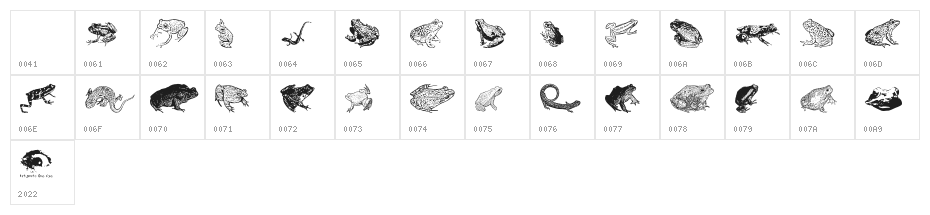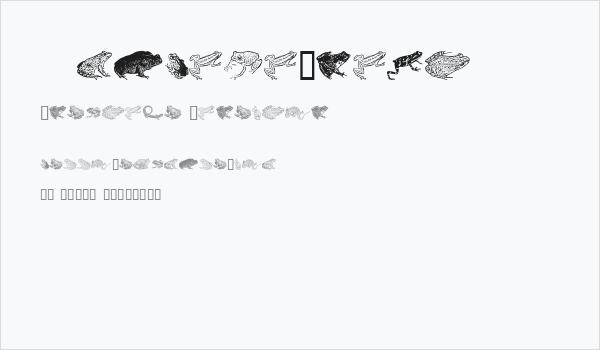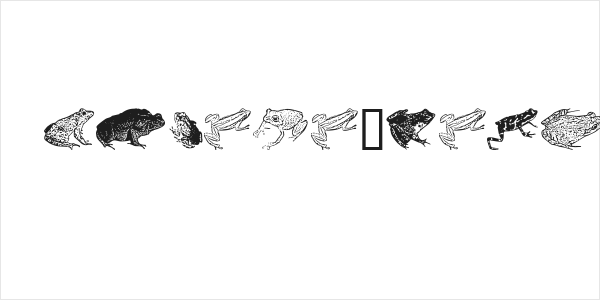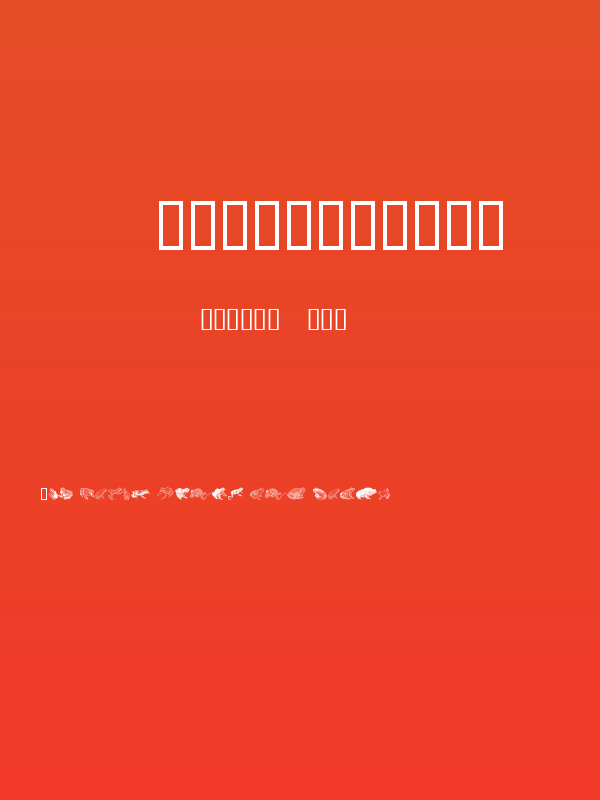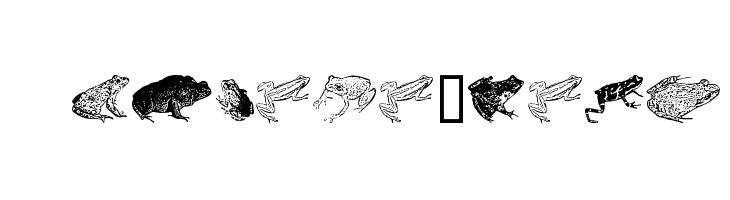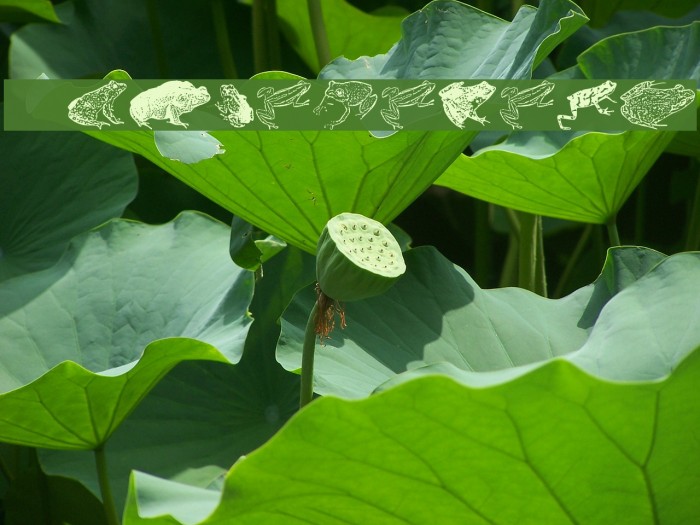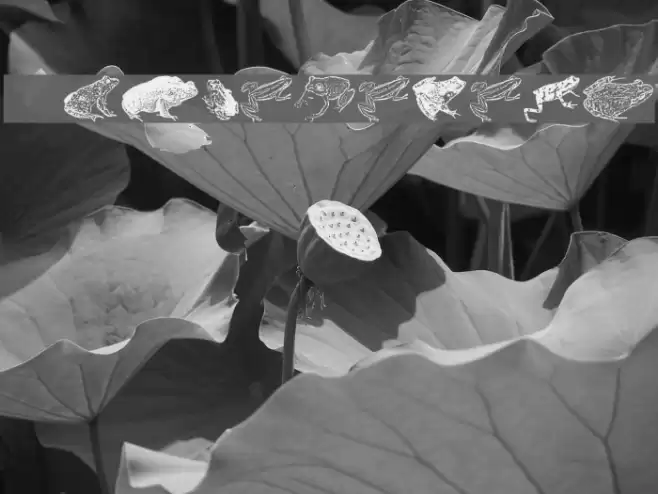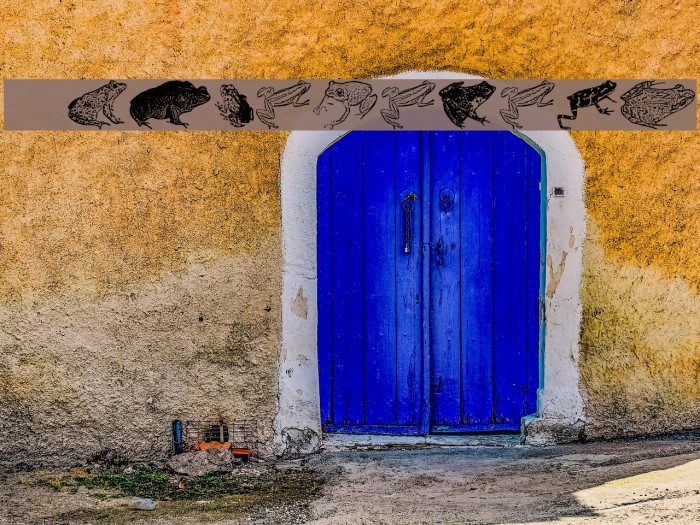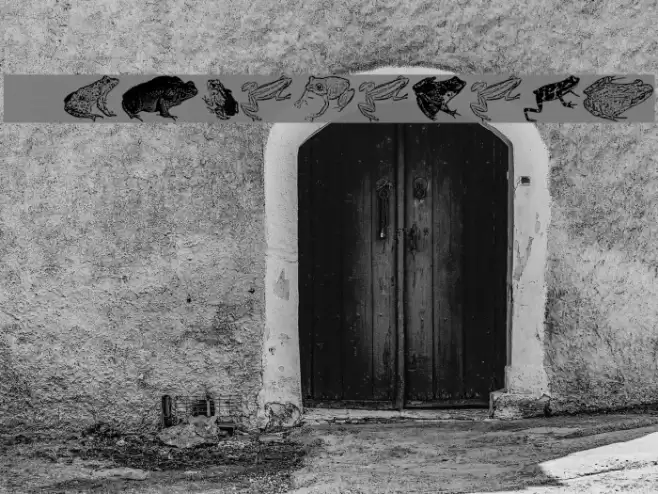
AmphibiPrint Font
| حالة الاستخدام | Logos, Posters, Artistic Designs |
| مشاريع مقترحة | Ideal for nature-themed projects, educational materials about amphibians, creative posters, and artistic designs that require a unique and illustrative touch. |